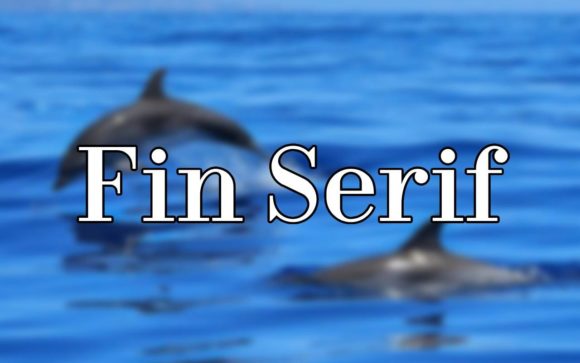
Fin Serif - Fonte serifada elegante para editoriais, ideal para revistas e blogs.
Fin Serif é uma fonte serifada refinada com um caráter clássico e moderno, apresentando serifas planas marcantes, traços de alto contraste e formas de letras bem equilibradas. Esta tipografia traz um toque de elegância e profissionalismo a qualquer projeto, seja para identidade visual, trabalhos editoriais, embalagens, logotipos ou materiais impressos. Como uma fonte serifada versátil, funciona perfeitamente tanto para textos de exibição quanto para textos corridos.
A fonte tem suas raízes na tradição da tipografia serifada, mas foi otimizada para a legibilidade moderna, tornando-a uma ótima opção para designers que valorizam tanto o charme estético quanto a clareza. A Fin Serif confere ao seu texto um toque atemporal e confiável, mantendo-se limpa e legível tanto na tela quanto na impressão.
- Estilos Regular e Itálico (família de fontes)
- Conjunto completo de caracteres latinos (incluindo pontuação, números, letras maiúsculas e minúsculas)
- Estética serifada atemporal — ideal para trabalhos de design elegantes e sofisticados.
- Versátil — funciona igualmente bem para aplicações de branding, impressas, editoriais e digitais.
- Alta legibilidade com caracteres claros e equilibrados.
- A combinação de um visual moderno com a tradição clássica das serifas proporciona flexibilidade em diversos estilos.
| Estilo Serif | Fonte serifada moderna com serifas planas e de alto contraste. | Serifa tradicional — traços serifados clássicos e contraste moderado. | Slab-serif — serifas mais grossas, estilo mais pesado |